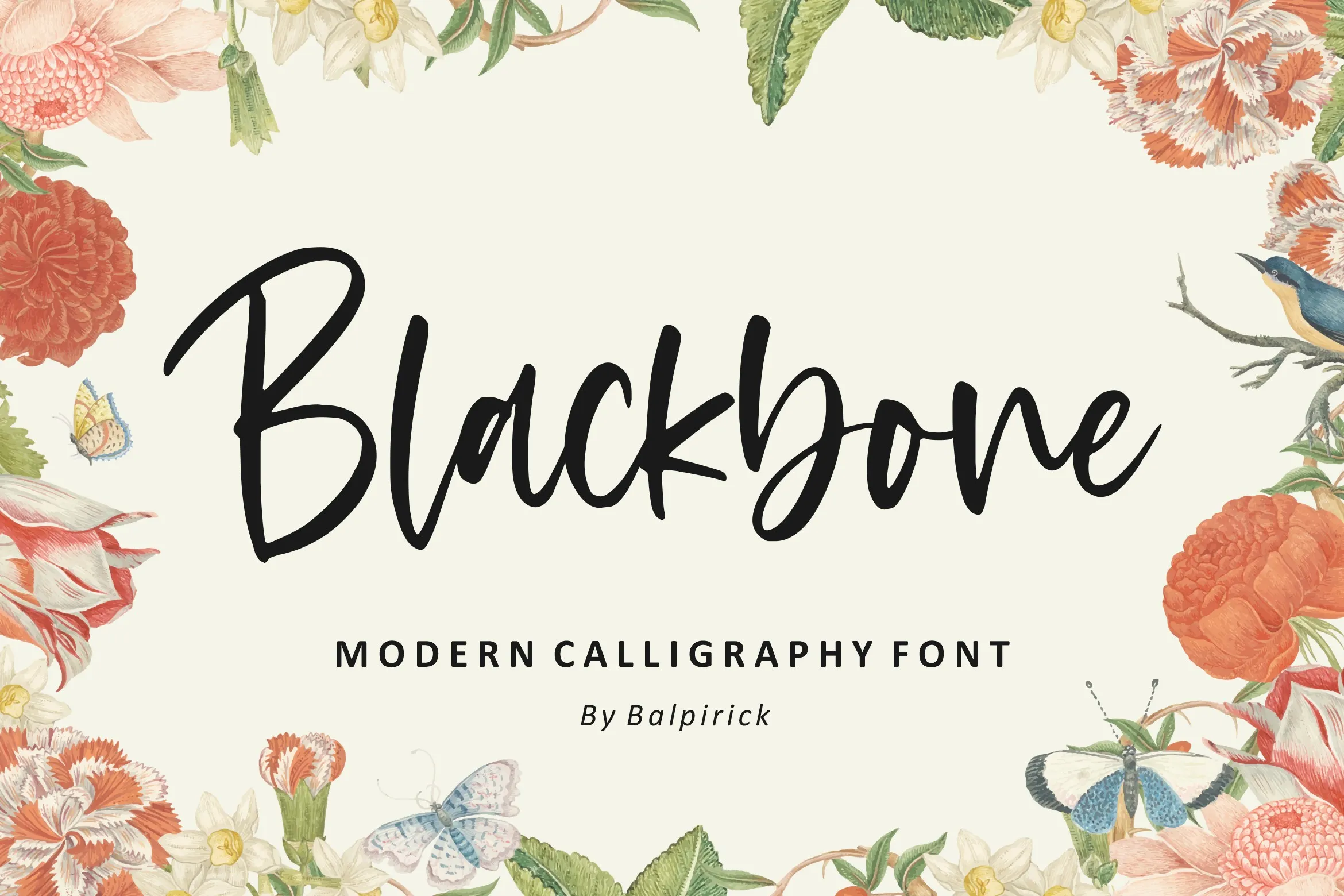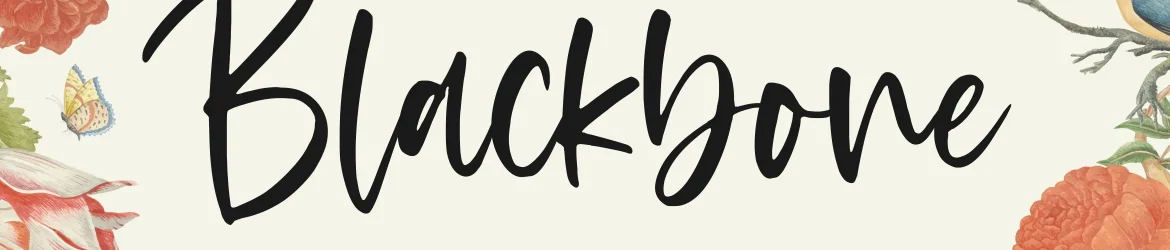
Introduzimos pela Balpirick Studio a Blackbone Modern Calligraphy Font, uma fonte de caligrafia moderna que transmite elegância e classe através de sua delicada escritura. Especialmente criada para pessoas que buscam um visual bonito e renovador em suas criações. Com o seu traçado único, esta fonte permite que qualquer projeto seja transformado com suavidade e sofisticação, tornando-o irresistivelmente atraente. Ideal para aqueles que desejam trazer uma pitada de delicadeza e classe aos seus designs digitais.